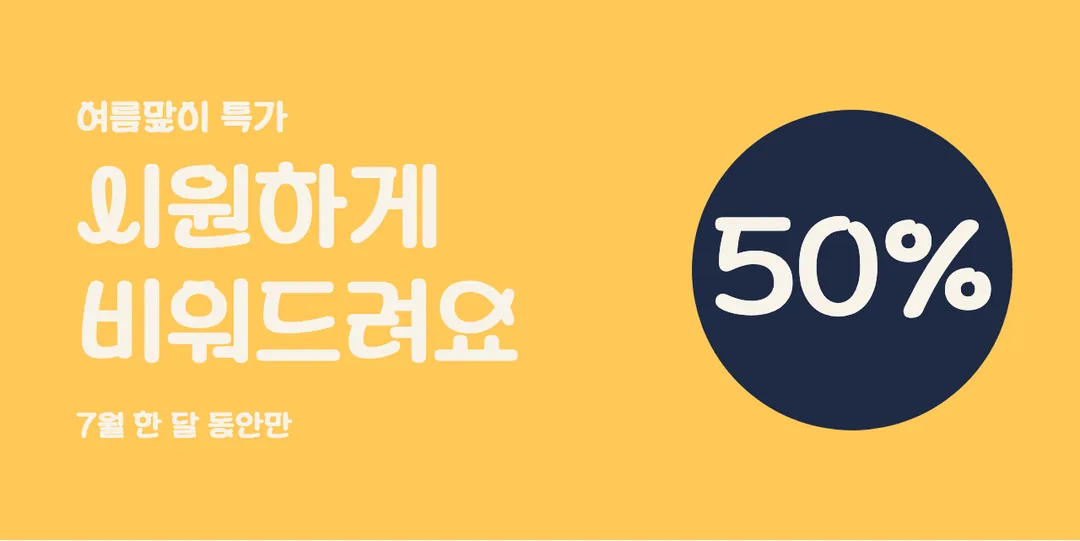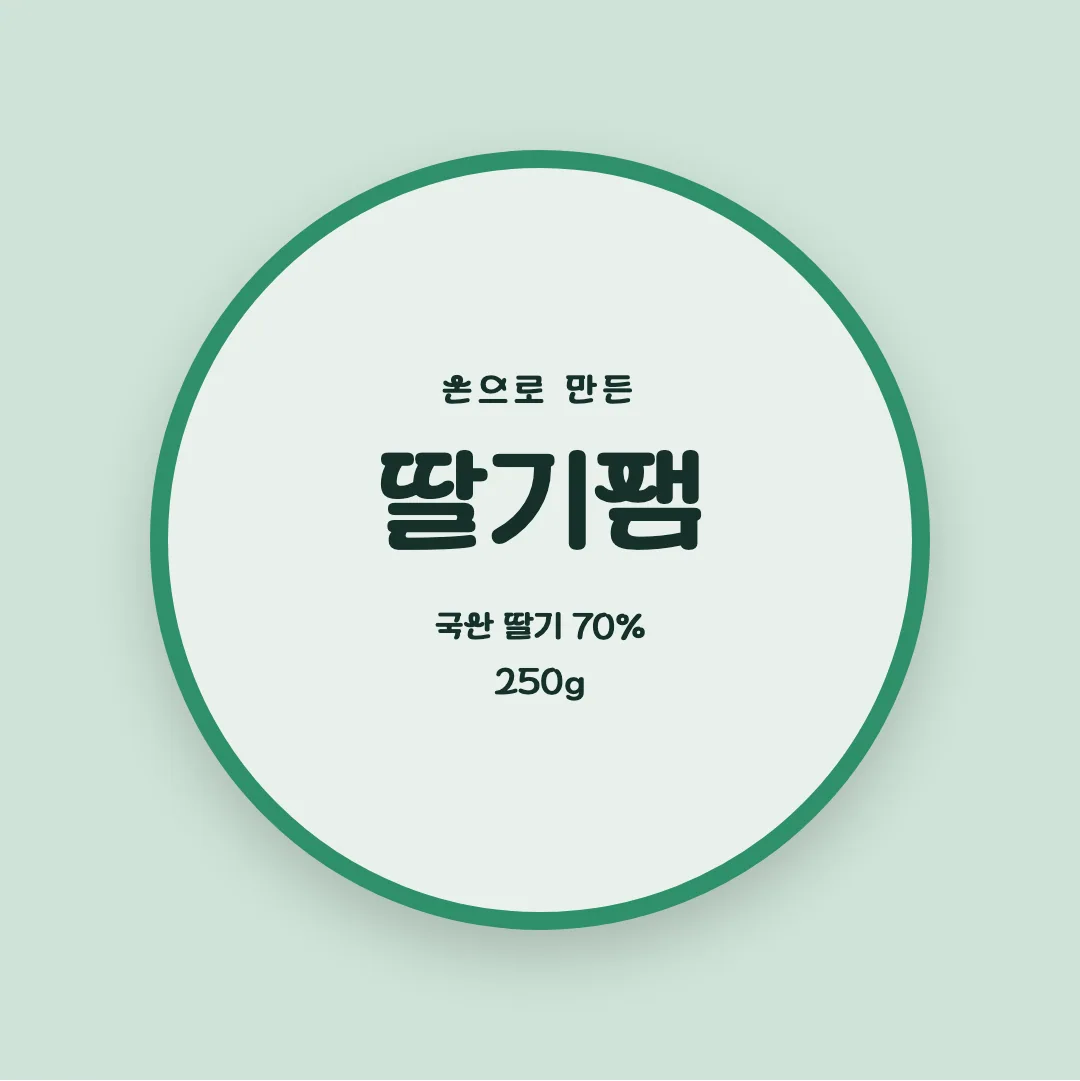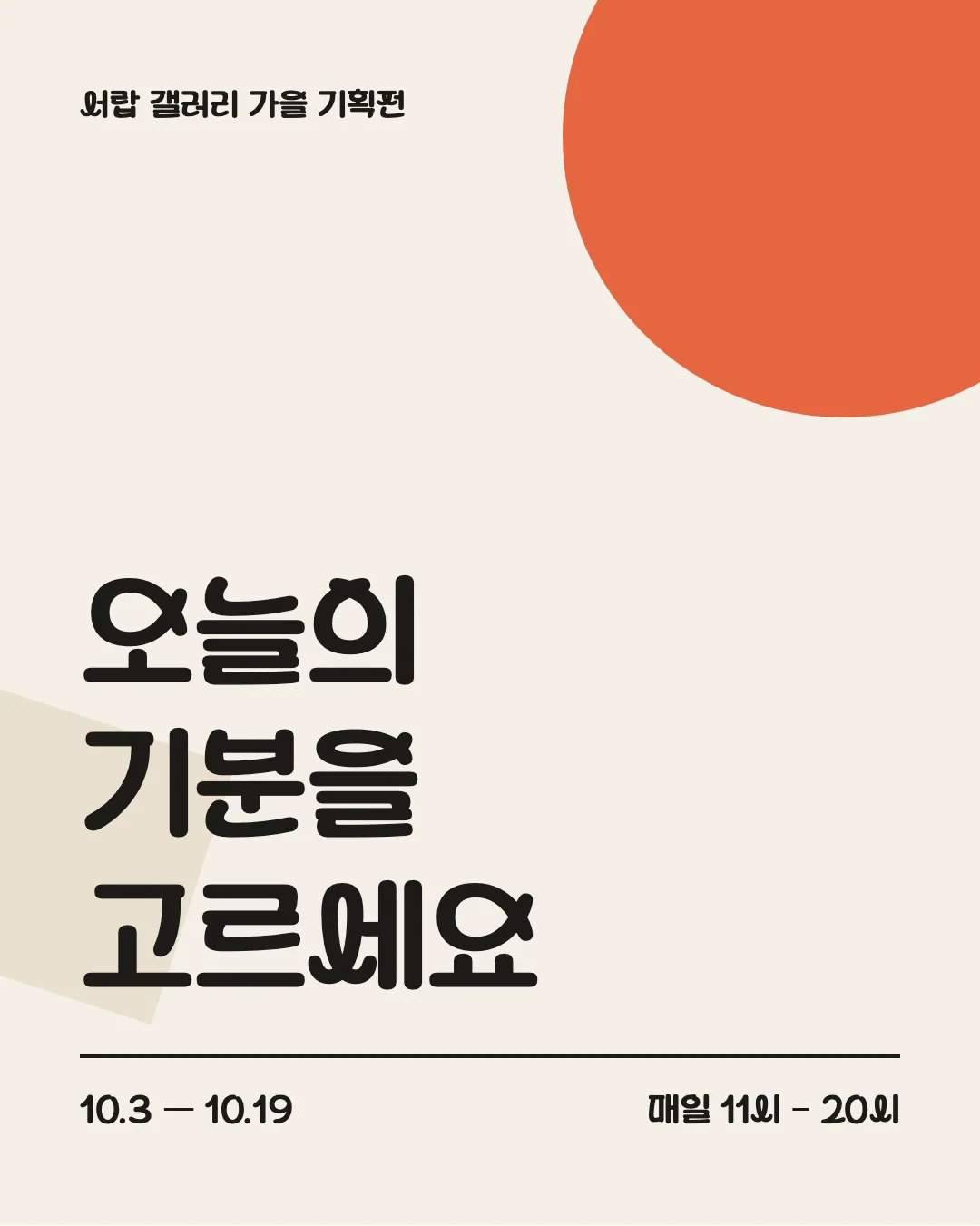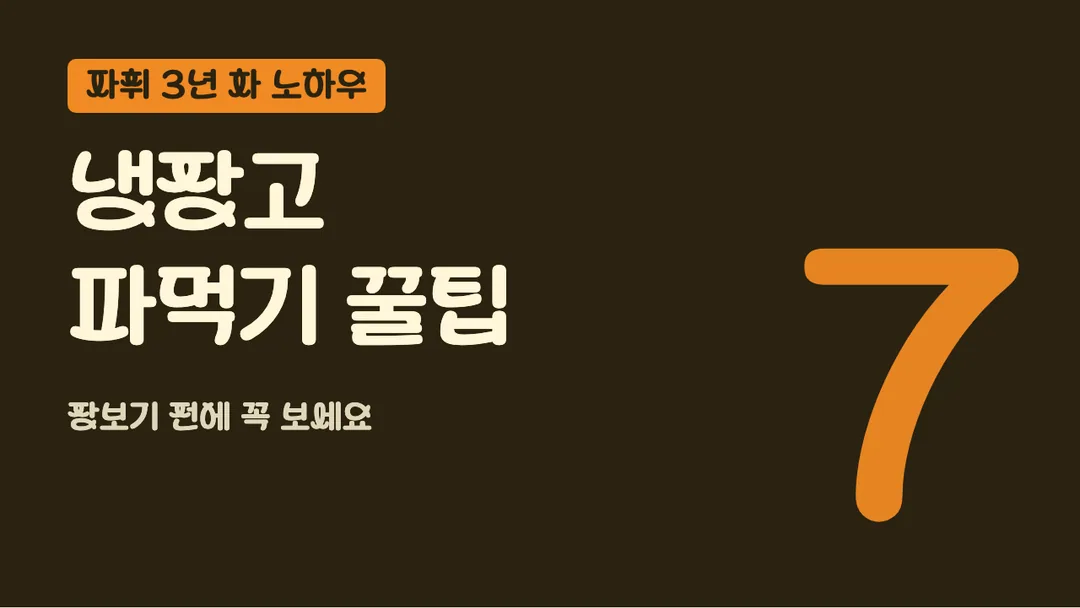
한국교육학술정보원(KERIS)이 배포하는 학교안심 폰트 중 제목용 서체입니다. 발표 자료나 포스터 제목처럼 눈에 띄어야 하는 곳에 좋습니다.
학교안심 꽈배기는 한국교육학술정보원 (KERIS)의 무료 장식체 폰트예요. 인쇄·웹사이트·포장지·영상·임베딩·BI/CI에 상업적으로 무료 사용할 수 있어요.